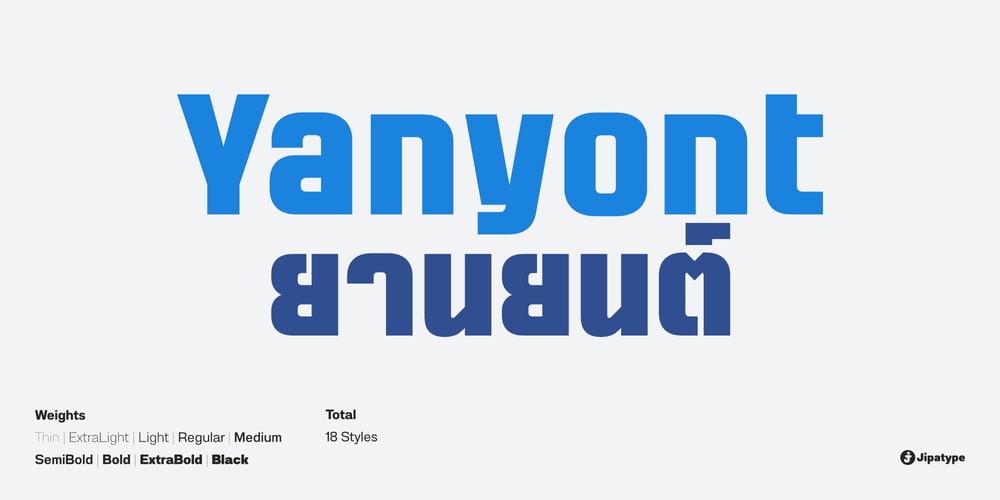
Yanyont Font Family was designed by Anupap Jaichumnan and published by Jipatype. Yanyont contains 18 styles and family package options. Yanyont แบบอักษรซานเซอริฟอเนกประสงค์และแห่งอนาคตที่สมบูรณ์แบบสำหรับอุตสาหกรรมยานยนต์ ด้วยฐานและ x-height ที่แบนราบ Yanyont มีรูปลักษณ์แห่งเทคโนโลยีอันโฉบเฉี่ยวที่ช่วยดึงดูดสายตาได้อย่างแน่นอน แบบอักษรได้รับการออกแบบด้วยรูปลักษณ์แห่งอนาคตแบบไซไฟที่เพิ่มความไฮเทคให้กับทุกโปรเจ็คของคุณ Yanyont มีน้ำหนักให้เลือกถึง 9 น้ำหนัก ทั้งแบบตัวตรงและแบบตัวเอียง รวมเป็น 18 ลักษณะให้ได้เลือกใช้ ซึ่งการมีตัวเลือกที่หลากหลายช่วยสร้างความเป็นอันหนึ่งอันเดียวกันในการสื่อทั้งหมดของคุณ ตั้งแต่โบรชัวร์และโปสเตอร์ไปจนถึงเว็บไซต์และแคมเปญโฆษณา นอกจากนี้ Yanyont ยังรองรับหลายภาษาและมาพร้อมกับคุณสมบัติ opentype เช่น Small cap หรือ tabular แบบอักษรนี้เหมาะสำหรับบริษัทที่มีการเข้าถึงระหว่างประเทศ ให้แบรนด์ยานยนต์ของคุณดูล้ำสมัยกับ YanyontIntroducing Yanyont, a versatile and futuristic sans-serif typeface that is perfect for the automotive industry. With its flat baseline and x-height, Yanyont has a sleek and technical look that is sure to catch the eye. The typeface is designed with a sci-fi futuristic look that adds a high-tech edge to any project. Yanyont offers 9 weight options in both upright and italic styles, for a total of 18 unique styles to choose from. This provides a wide range of options for creating a cohesive look across all your branding materials, from brochures and posters to websites and advertising campaigns. Additionally, Yanyont supports multiple languages and come with opentype features such as small cap or tabular. This typeface is perfect for companies with international reach. Give your automotive brand a cutting-edge look with Yanyont.